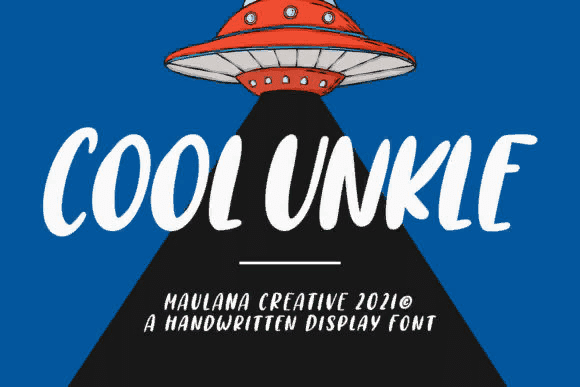
Название: Cool Unkle Font (2021)
Описание:
Cool Unkle - это игривый, причудливый и матовый шрифт.
Если вы используете его для дизайна, связанного с мультфильмами, детскими играми или просто для любого творения, требующего милого прикосновения, этот шрифт станет отличным выбором.
Название: Cool Unkle Font (2021)
Описание:
Cool Unkle - это игривый, причудливый и матовый шрифт.
Если вы используете его для дизайна, связанного с мультфильмами, детскими играми или просто для любого творения, требующего милого прикосновения, этот шрифт станет отличным выбором.